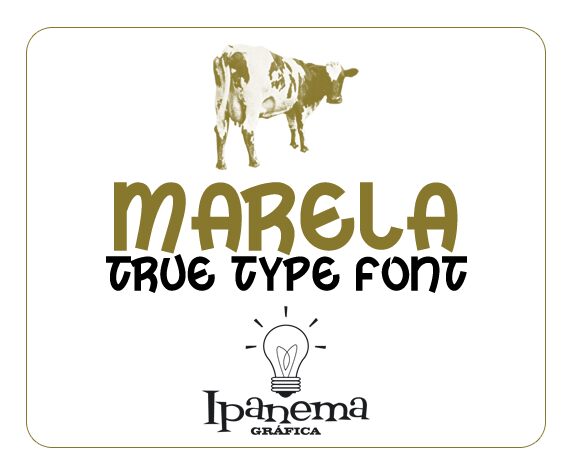
Marela od Ipanema Grfica to darmowy krój displayowy w komiksowym stylu, charakteryzujący się zaokrąglonymi, nieregularnymi literami o rytmie przypominającym ręczne wycinanie. Kształty swobodnie się wyginają i pochylają; niektóre znaki tworzą szerokie łuki, podczas gdy inne zachowują proste boki i zdecydowane cięcia.
Marela świetnie sprawdza się w tytułach plakatów, ulotkach, brandingu dla dzieci, na opakowaniach, w krótkich logotypach oraz jako zabawny akcent w projektach edytorskich. Nieregularne kształty nadają krótkim frazom swobodny, ręcznie robiony charakter, nie tracąc przy tym wyrazistości niezbędnej w krojach nagłówkowych.